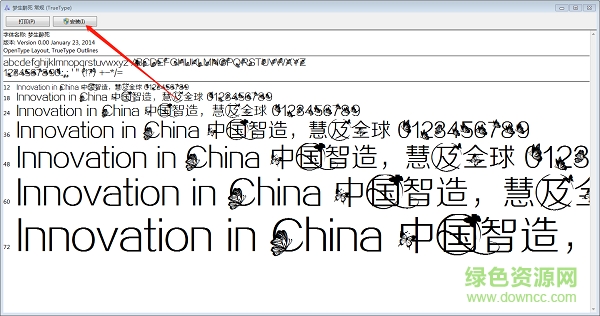
夢死醉生字體是一款筆鋒教細(xì),看起來比較剛硬,但是設(shè)計(jì)者又在字體中增加了部分卡通圖案,讓整個(gè)字體看起來有一絲絲的俏皮,適用于眾多的素材之中,需要的用戶快來綠色資源網(wǎng)下載吧!
夢死醉生字體是一款漂亮的中文藝術(shù)字體,不僅擁有簡潔美觀的字體外觀,還加入了多種卡通圖案,還有大量蝴蝶圍繞著字體翩翩飛舞,讓字體看起來有一種夢幻般的感覺,支持多種字體輸出格式,完全能滿足日常使用需求,適合應(yīng)用在廣告、設(shè)計(jì)、網(wǎng)站、雜志中使用。